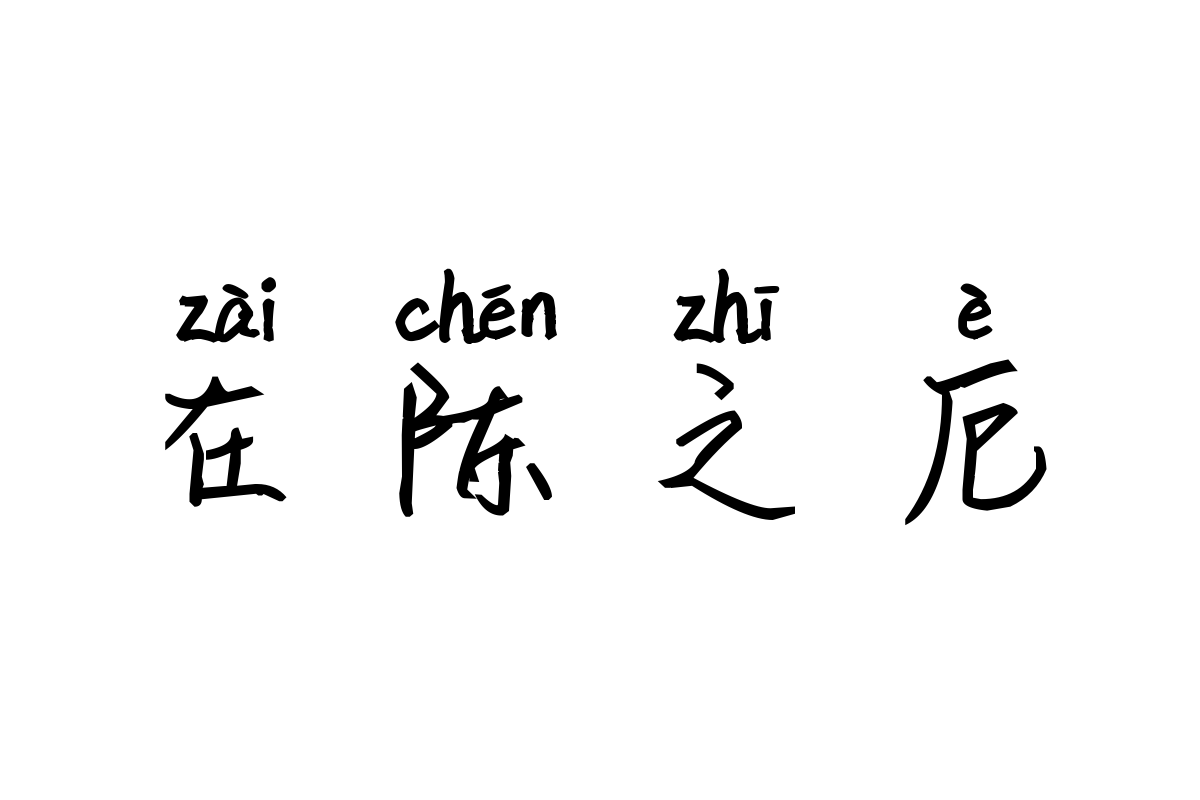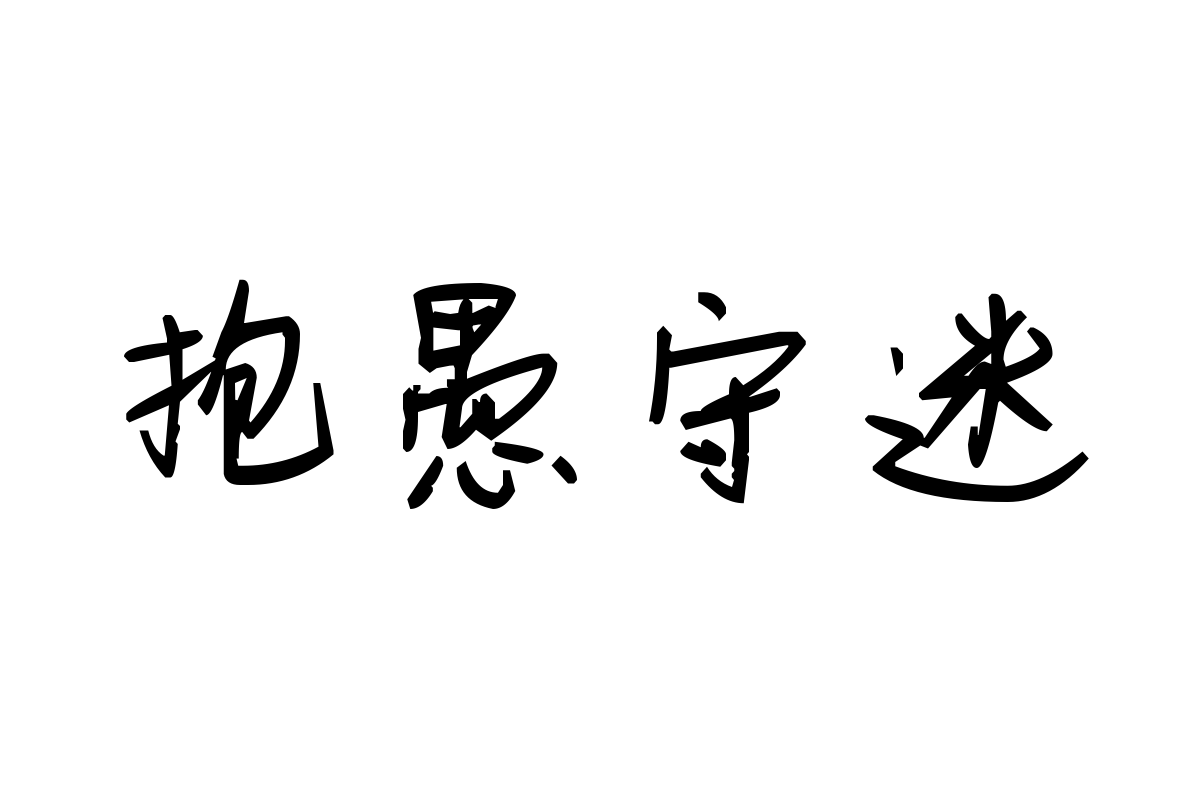
米开从你的全世界路过是一款中文字体,由上海仪旗信息技术有限公司设计。这款字体具有独特的艺术风格和强烈的视觉冲击力,适合用于各种商业、广告、设计等领域。
米开云汐拼音体的主要特点包括:
1. 字形结构:字体采用了独特的笔画结构和布局方式,使得每个字符都呈现出独特的美感。这种结构不仅使得字体看起来更加美观,还有助于提高阅读舒适度。
2. 笔画粗细:字体中的笔画粗细变化丰富,从细到粗再到细,形成了一种动态的视觉效果。这种变化不仅增加了字体的层次感,还使得整体视觉效果更加生动有趣。
3. 字形风格:字体的风格独特,既有传统的韵味,又不失现代感。这使得字体在各种场合都能得到广泛的应用,无论是平面设计、广告宣传还是网页设计等。
4. 可读性:虽然米开云汐拼音体在视觉效果上非常出色,但同时它的可读性也非常优秀。字体的大小、间距等设置都非常人性化,方便用户在不同场景下进行阅读。
总之,米开云汐拼音体是一款集美观、实用与创新于一体的中文字体,适合用于各类设计项目,为设计师提供了一个全新的视觉选择。
米开云汐拼音体
米开从你的全世界路过